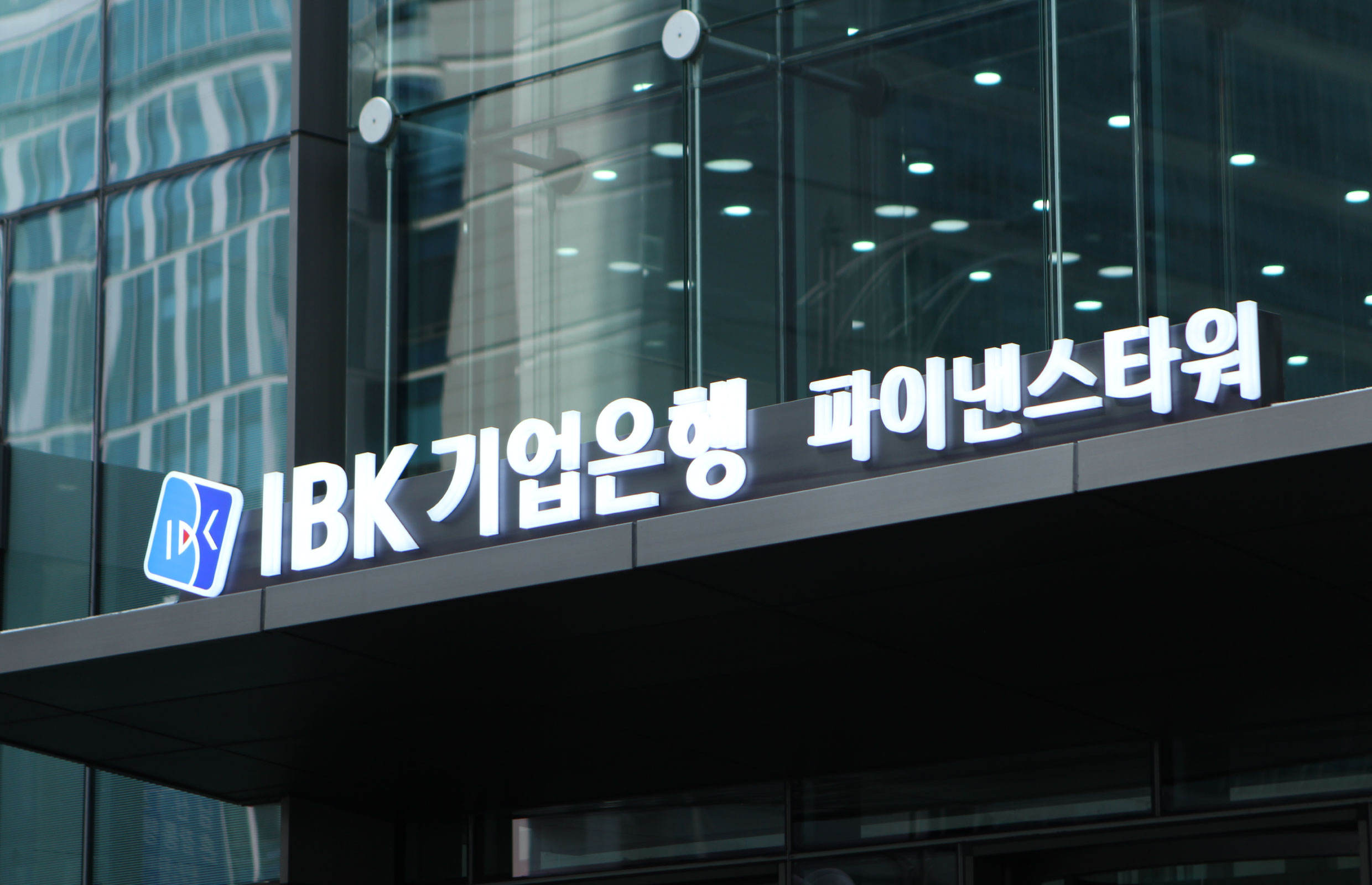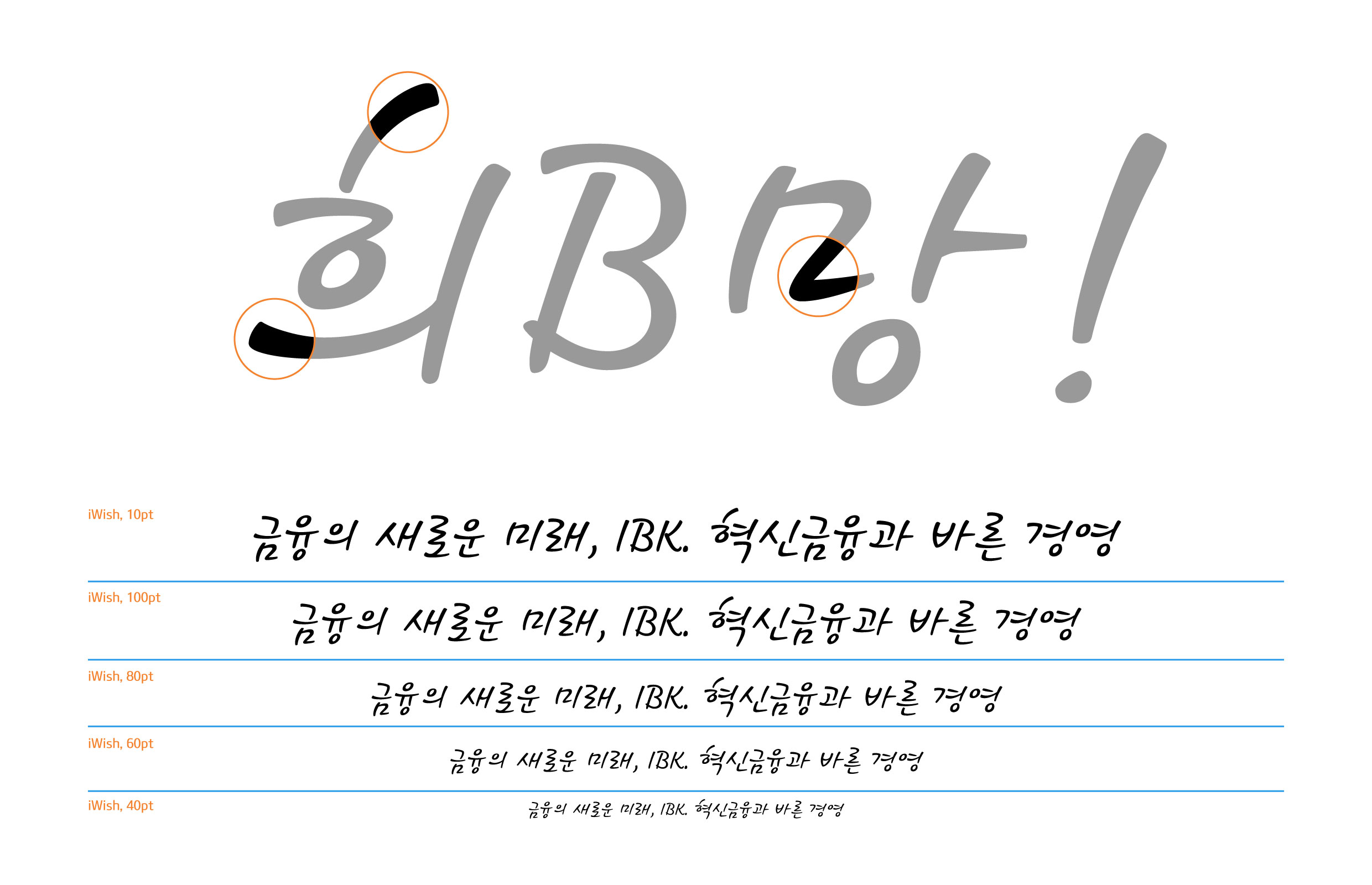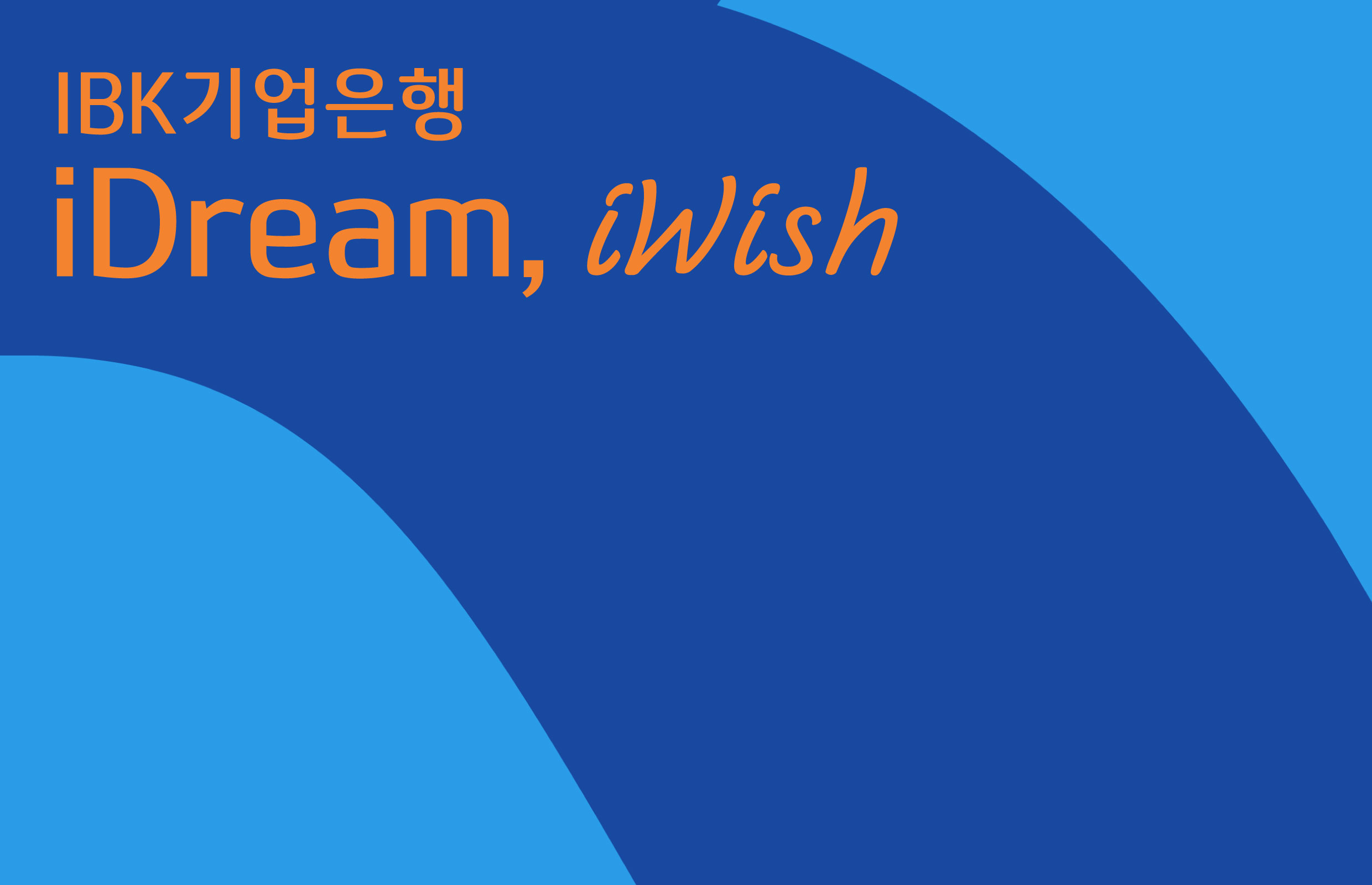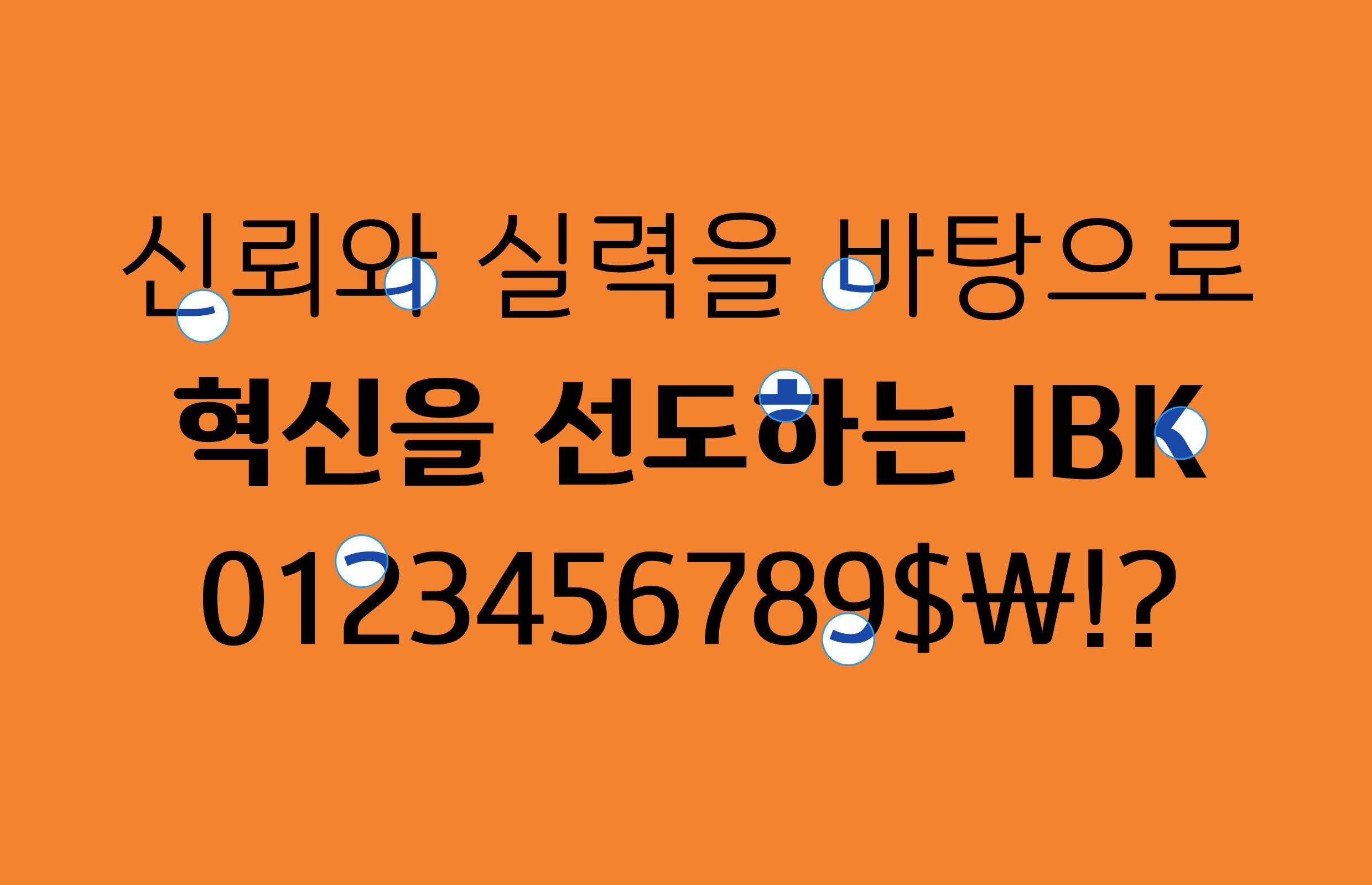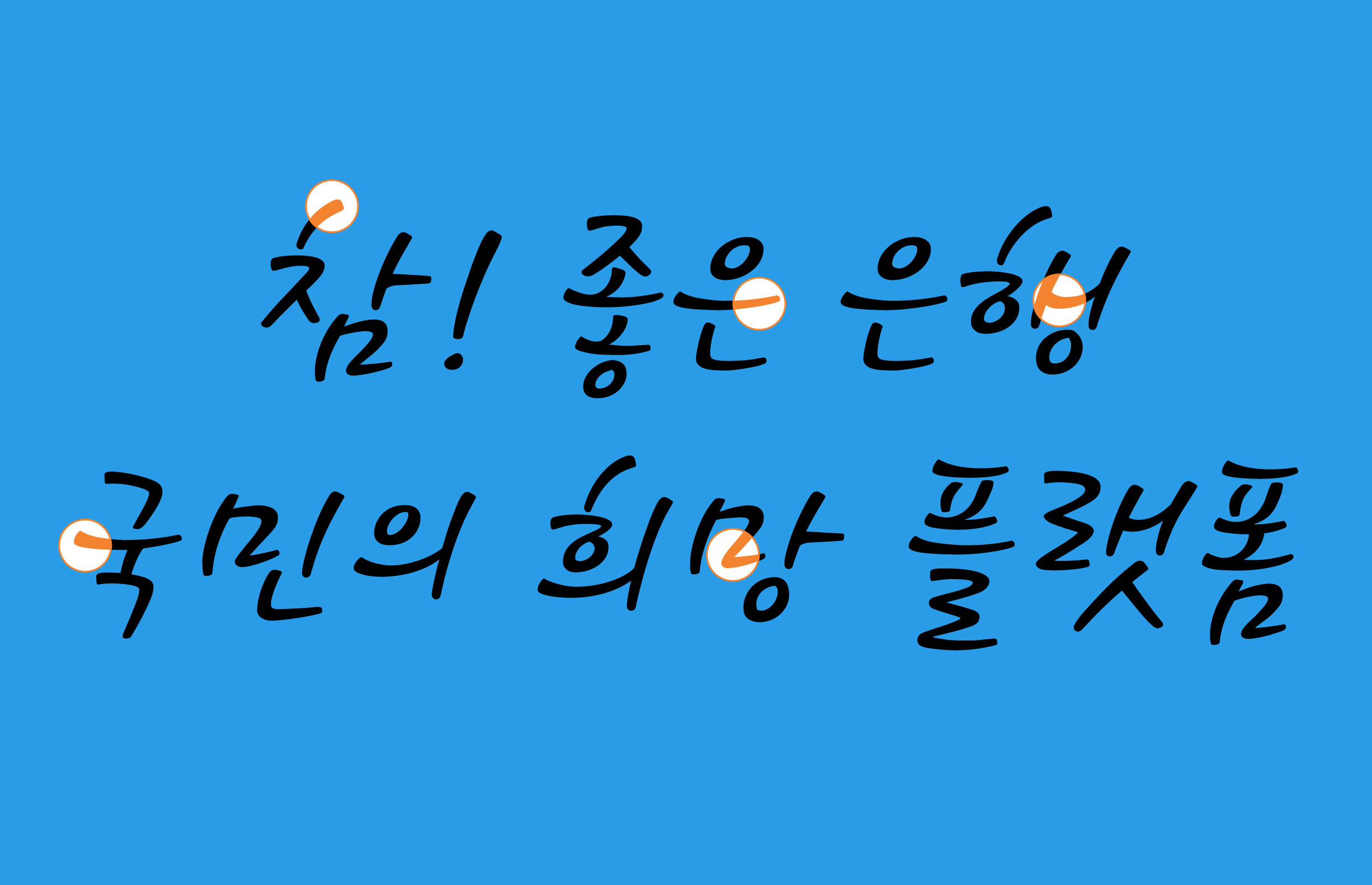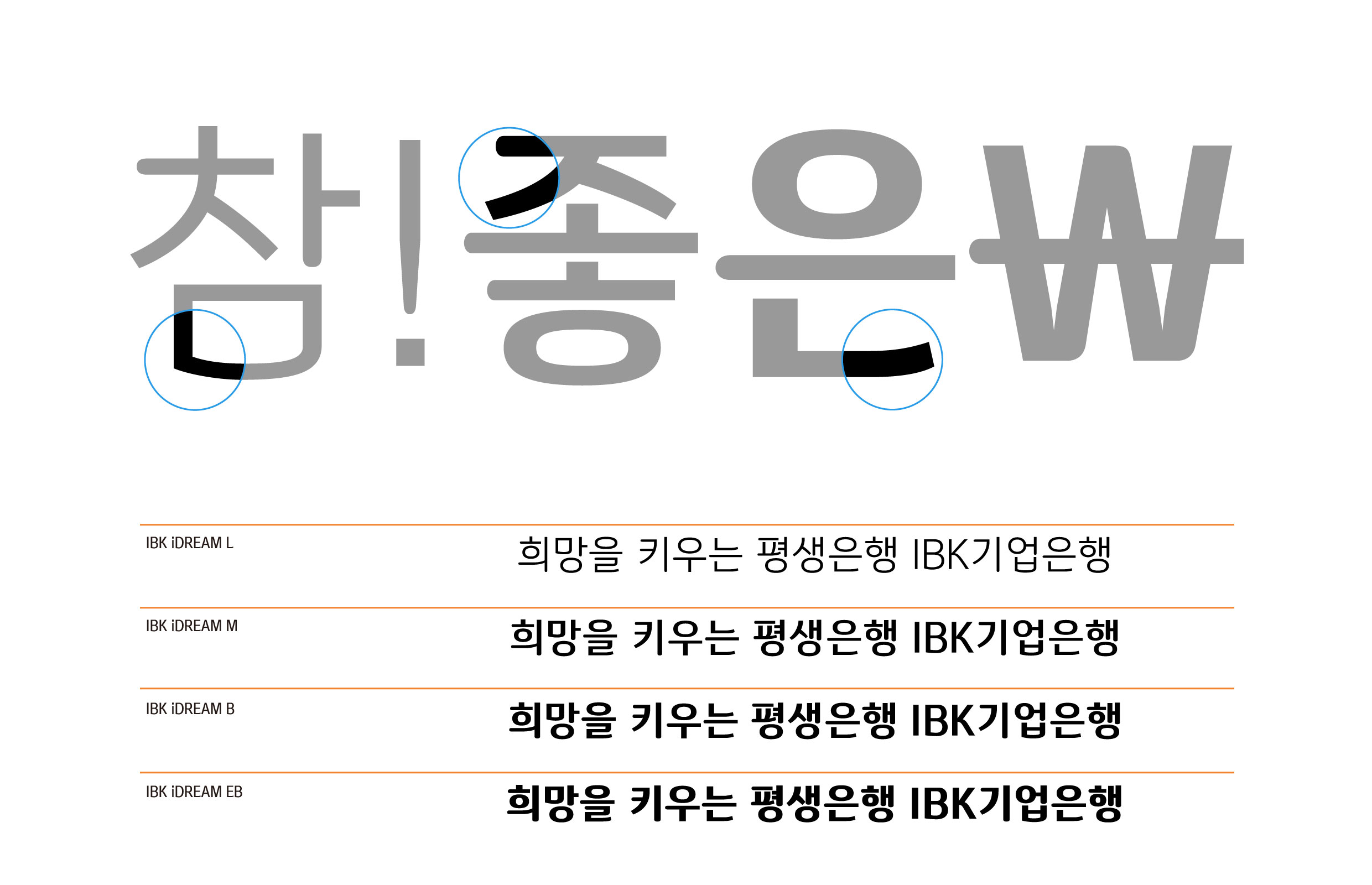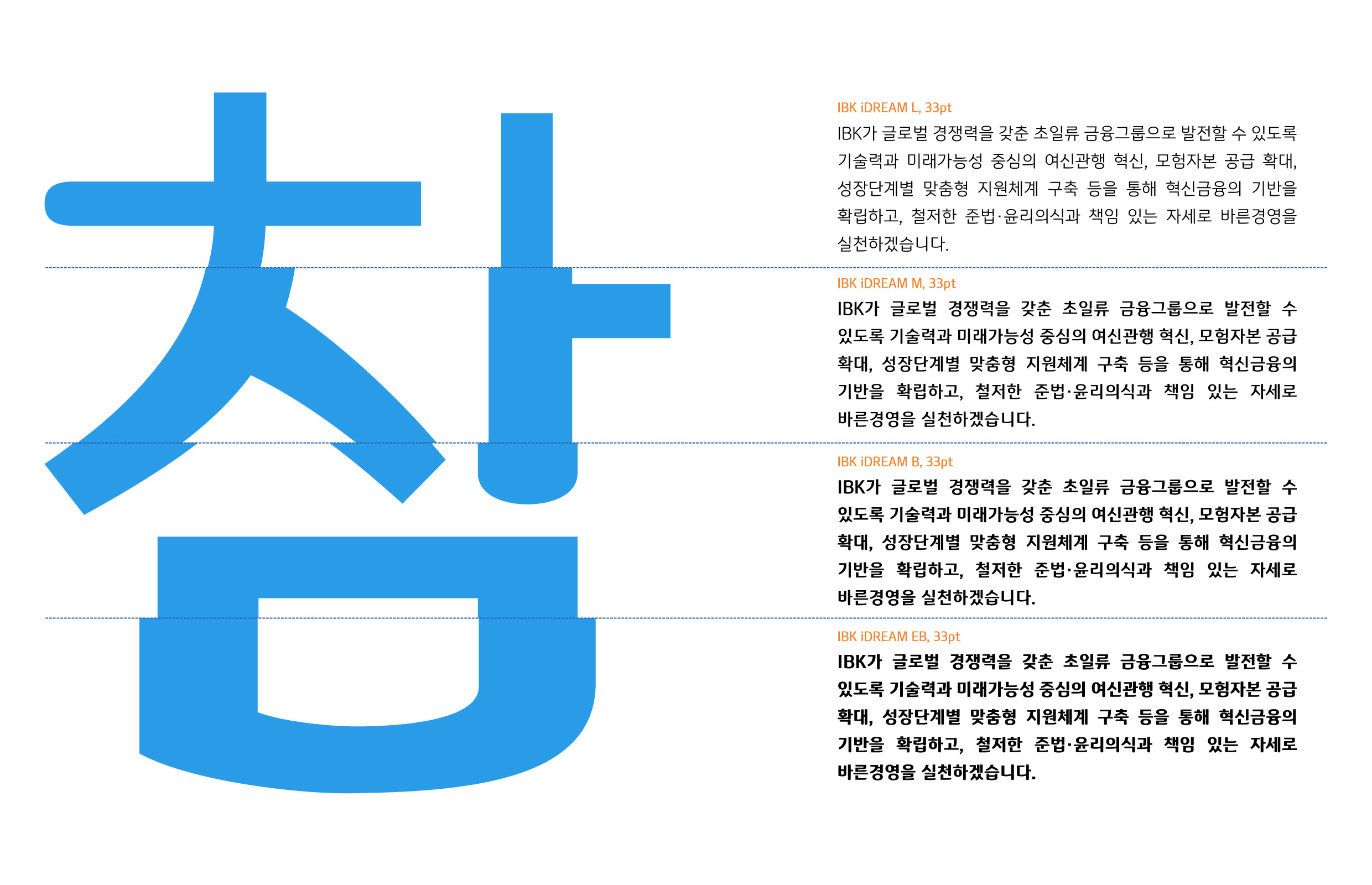
IBK 기업은행 [아이드림, 아이위시]
‘드림(dream)’과 ‘위시(wish)’라는 서체명에서 알 수 있듯, IBK기업은행이 추구하는 ‘고객의 꿈과 바람’, 그리고 브랜드 슬로건인 ‘희망금융’을 글자로 표현했다. 고딕체인 ‘아이드림’은 지적이고 신뢰감을 주는 이미지를, 손글씨 서체인 ‘아이위시’는 친근한 정서를 부각했다.